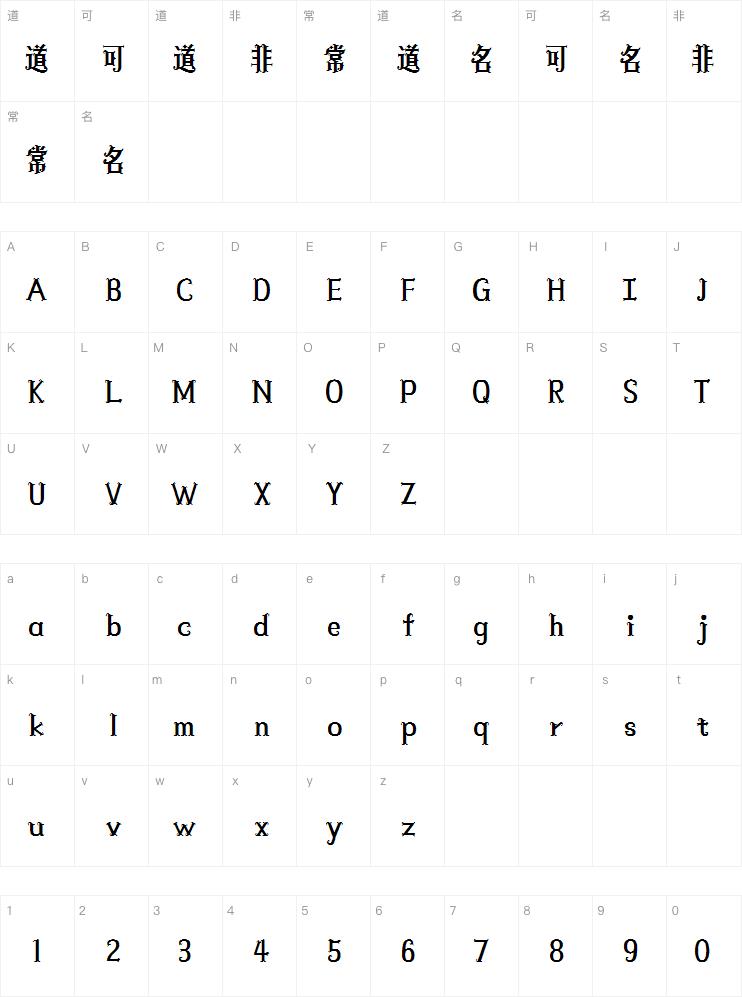
山海精灵物语,是一款全新的字体,包含汉字9169个,符号200+个。该字体是一款卡通风哥特字体,该字体融合了西方哥特元素,字体独特,新颖华丽。这款字体有着很强的装饰性和醒目的视觉效果,字体重心略微偏上、结构空间均衡、字面趋于瘦高长方形,整体感觉稳重规整。字形灵动多变,童趣可爱,同时融入花型起头和结尾,装饰性十足,带给人魔幻、华丽的视觉感受。撇和捺作为字形中延展性最高的两个笔画,形态华丽灵动。整体笔触圆润,活泼清新,造型生动有趣,具有灵活的适用性,天真俏皮又不失时尚感。在体现哥特风格的同时呼应了中文的笔画特征,并在设计上有意改善传统哥特体复杂难辨认的特性,尽量做到易辩、易读,保证了字体的实用性。汉字艺术与西方文字的融合,如精灵国度般华丽高贵,又宛如梵高的《星月夜》般神秘梦幻;个性鲜明的字体特征,散发着神秘而华丽的气息。在华丽而不失婉约中,感受哥特风的魅力。